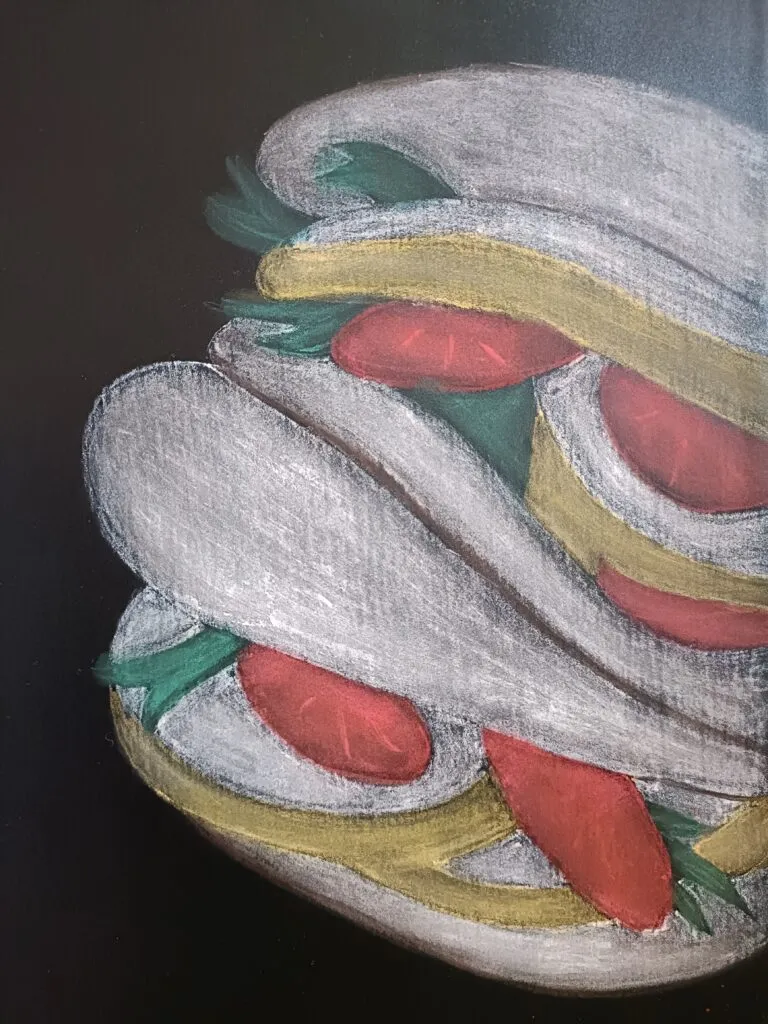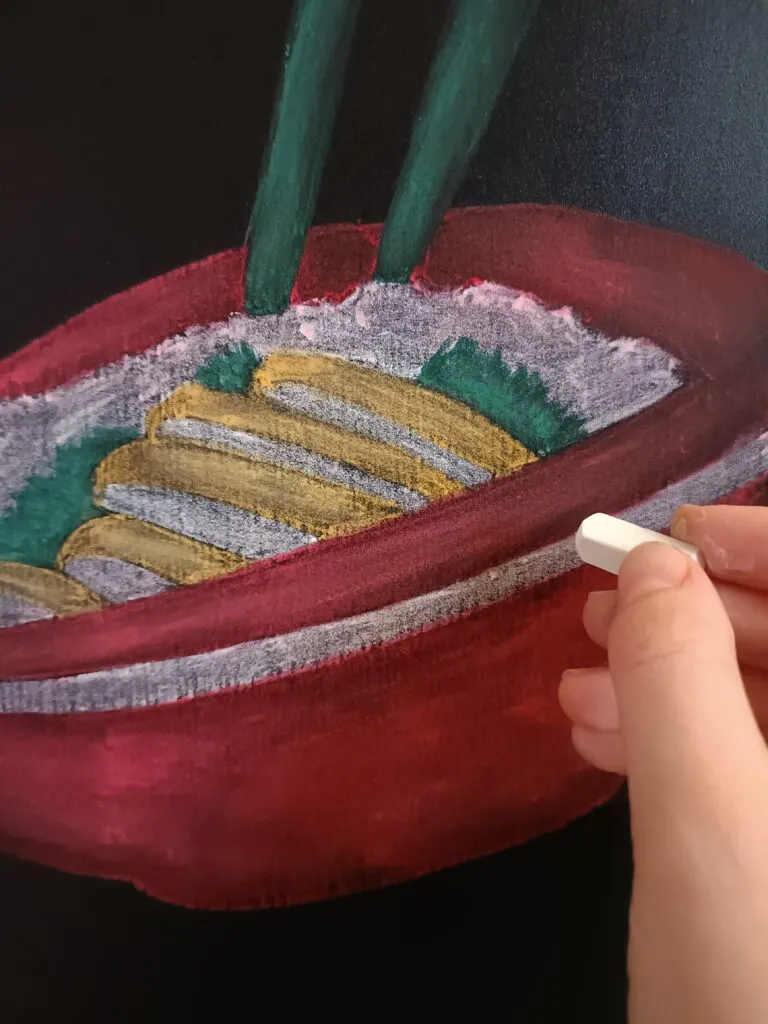
Ardoise
Bao House – Les 500
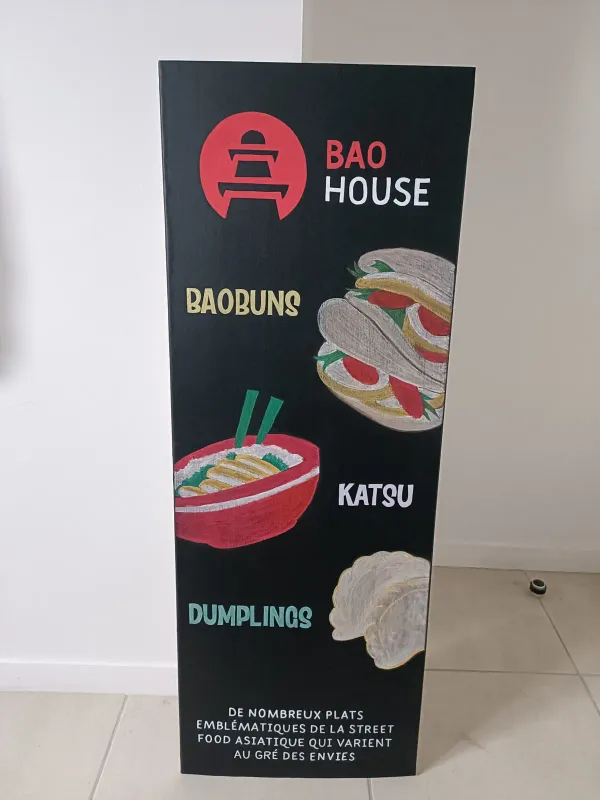
À propos du projet
Création graphique et peinture aux feutres acryliques et pastel du menu ardoise du nouveau stand de street food aux 500.
Bao House